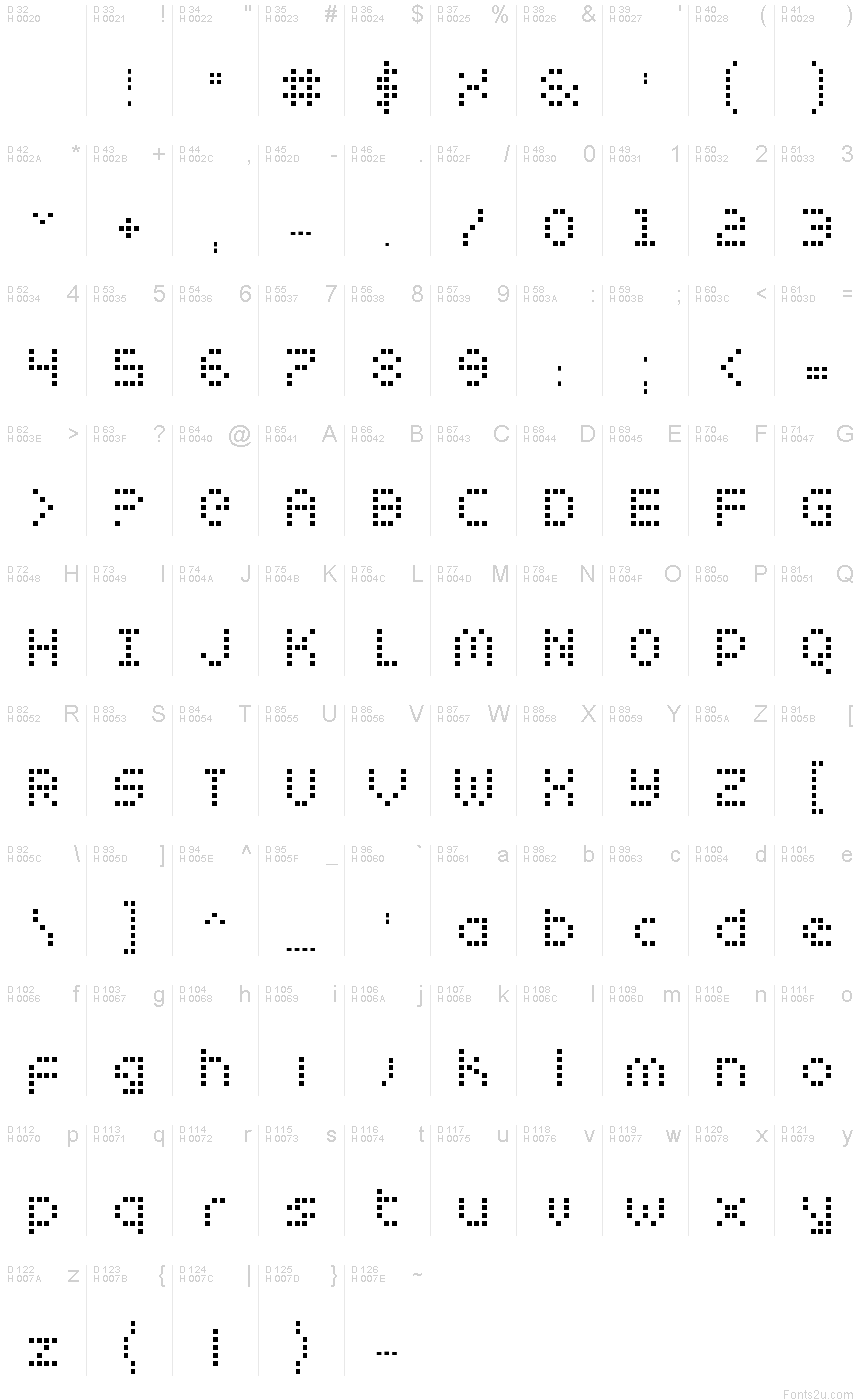
Zado Bold od Iconian Fonts to darmowy cyfrowy font typu display o solidnym bitmapowym rytmie i zabawnej arcade’owej energii. Litery zbudowane są z kwadratowych modułów i krótkich, przełamanych kresek, co nadaje krojowi celowo „niskorozdzielczy” wygląd, przywodzący na myśl raczej wczesną grafikę komputerową niż sterylny futuryzm.
Dzięki temu świetnie sprawdzi się w logotypach gier, plakatach retro-tech, ulotkach muzycznych, nakładkach do streamingu czy planszach tytułowych – wszędzie tam, gdzie darmowy font ma wnieść trochę pixelowego charakteru bez zbędnego zadęcia. Dobrze wypada też w krótkich nagłówkach i etykietach stylizowanych na interfejsy, ponieważ stopniowane formy i powtarzalny blokowy wzór sprawiają, że tekstura jest żywa nawet przy zaledwie kilku słowach.
Zado Bold